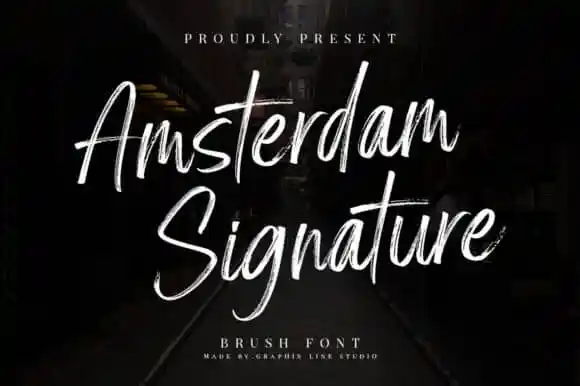
Amsterdam Signature Brush Font – Download Grátis
A Amsterdam Signature Brush Font é uma elegante seleção para aqueles que buscam um efeito despojado nas criações digitais, especialmente na área dos logotipos e marcas de água para fotografias ou marca pessoal. Criada pela Graphix Line Studio, essa fonte especial foi desenvolvida usando uma lousa seca, resultando em um tipo de letra casual mas extremamente versátil e fluido. Este estilo de tipo não só oferece uma arrumação cuidadosa dos caracteres, mas também adiciona um toque de frescura à sua marca ou logotipo, tornando-a única e imediatamente reconhecível. Composta por linhas suaves e letras perfeitas, esta fonte é adequada para uma variedade de aplicações, desde criação de materiais de marketing até projetos pessoais que buscam um touch diferenciado. Seja você um designer ou criador de conteúdo, a Amsterdam Signature Brush Font é definitivamente o tipo certinho para aqueles buscando uma fonte elegante e despojada com um toque de personalidade única.